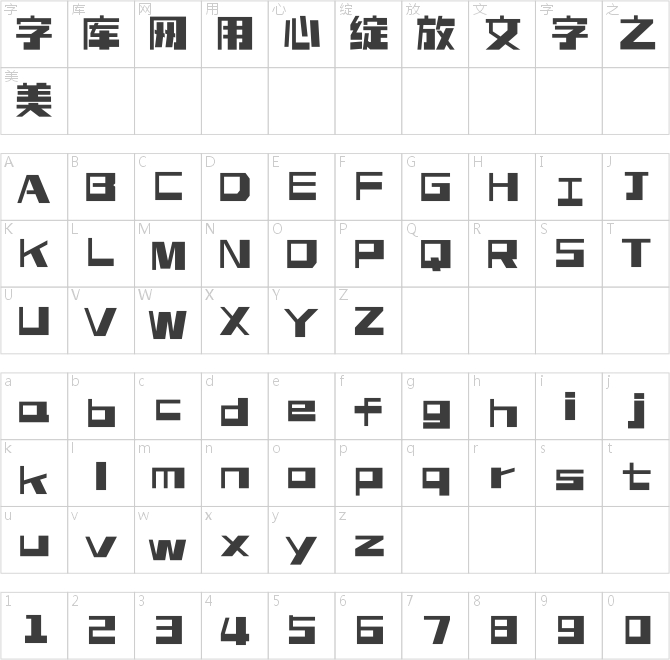
字体名称: 造字工房汉方体
造字工房汉方体
造字工房汉方体介绍
造字工房汉方体,字形设计中宫宽大,笔画左细右粗,搭配巧妙,疏密得宜,留白均匀。风格稳重有力、工整硬朗,结构醒目有力,引人注目,富有时代感,迎合了现代的审美观。它适合用于标题、广告语、时尚刊物、名称等主信息文字的设计。本字体为简体字库,采用OpenType/CID格式,Adobe-GB1-5编码。基于中华人民共和国GB2312-80字符集标准,另按需添加101个汉字。共收容字数6864CJK汉字,ASCII常用字符100个。